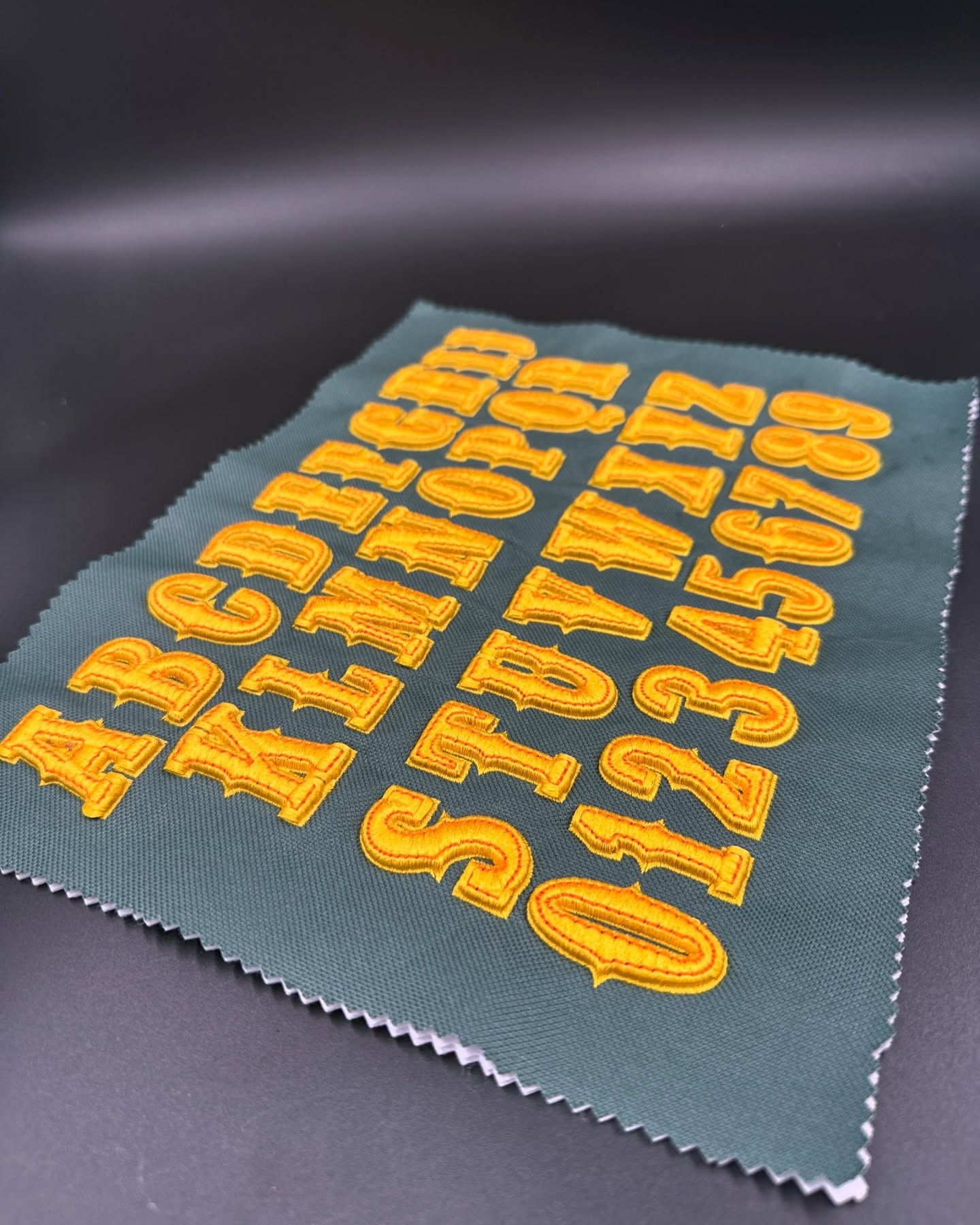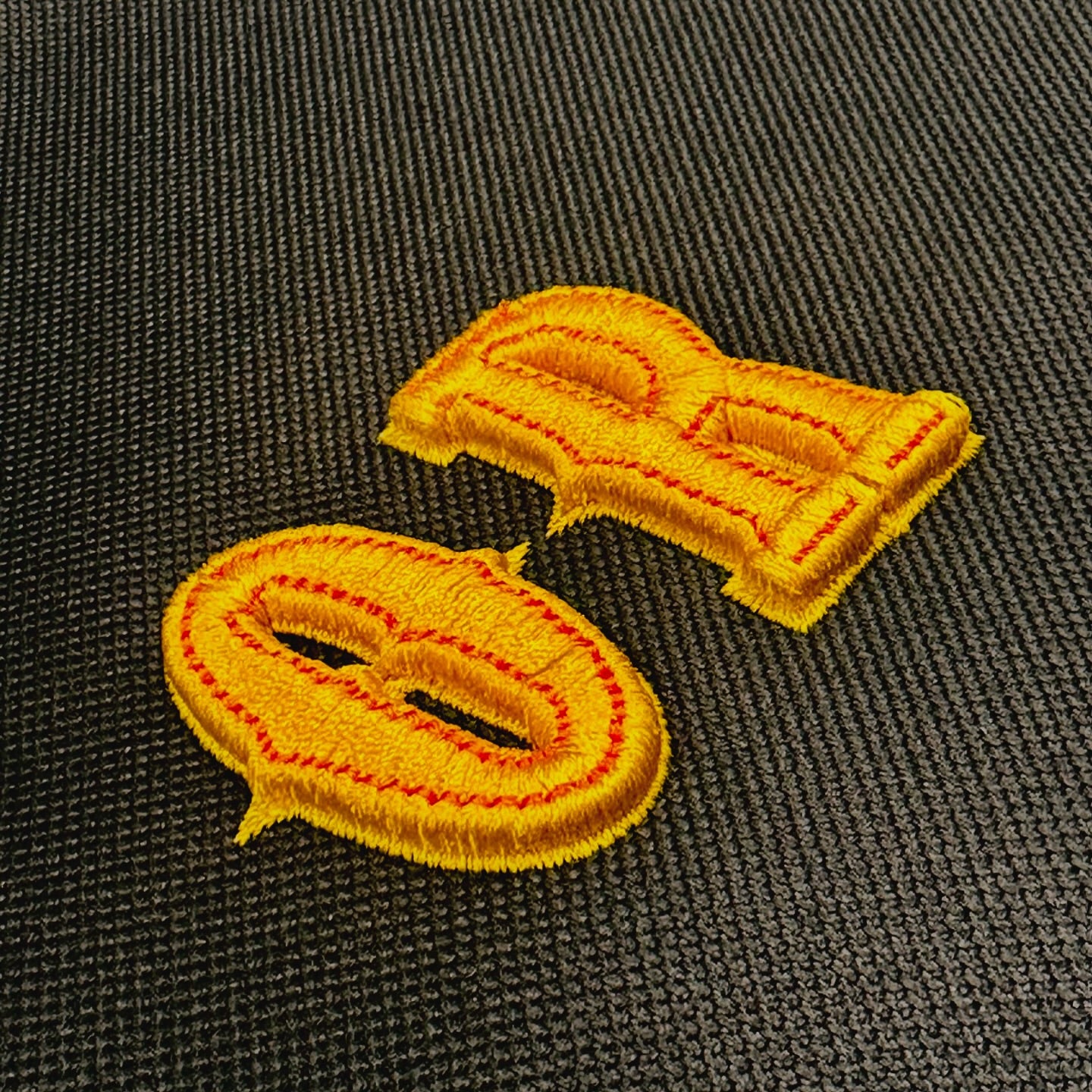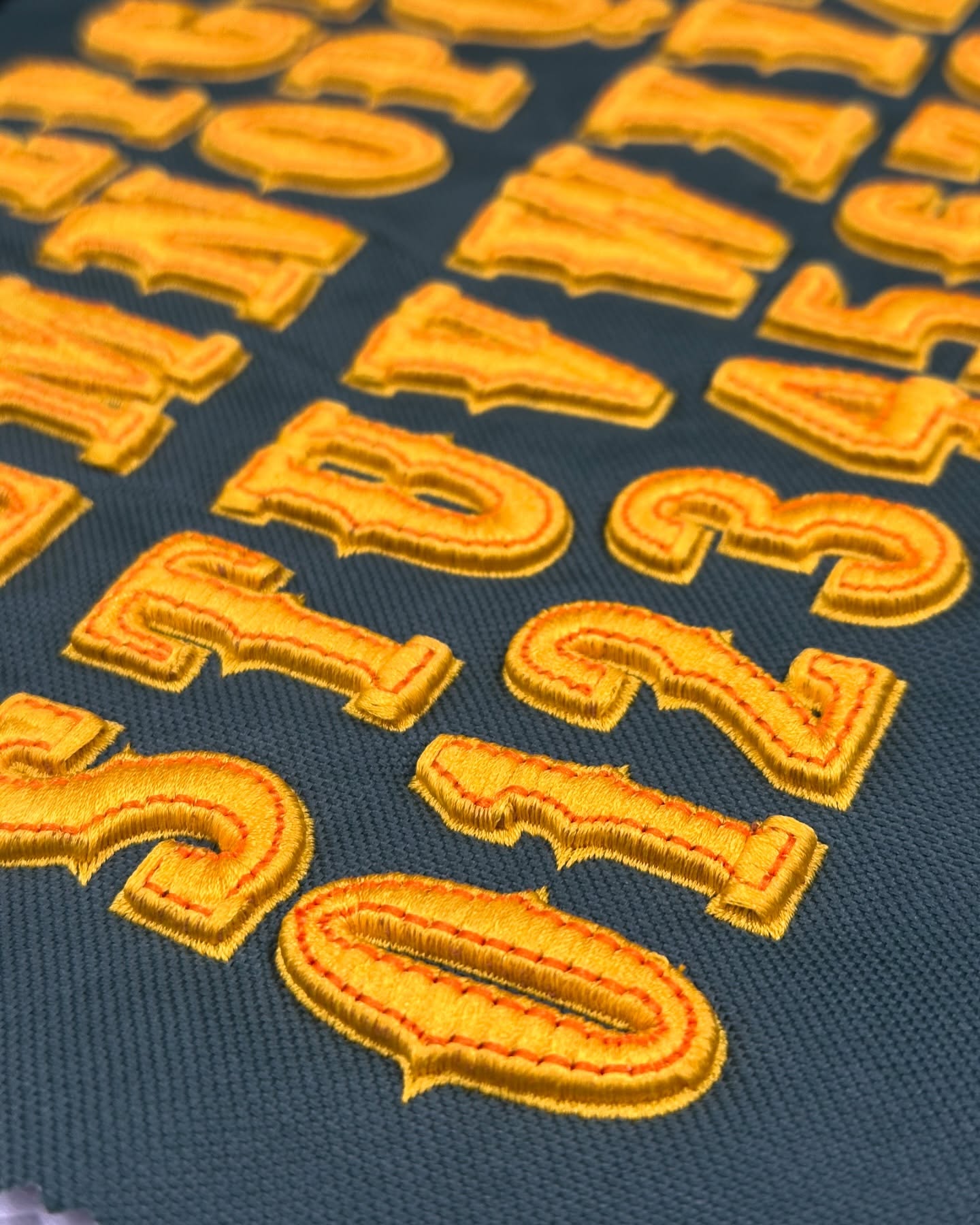
خط تطريز Western Rodeo – أحرف وأرقام عتيقة جريئة
خيوط متعددة الأوجه: حيث تتألق الحروف كالألماس ✨
قم بتحويل النص العادي إلى فن يمكن ارتداؤه بشكل مذهل باستخدام تطريز فاخر بخطوط ماسية . مستوحى من الزوايا الدقيقة للأحجار الكريمة المقطوعة، كل حرف ورقم من الأبجدية مطرز بدقة بخيوط ثقيلة، مما يخلق جوانب هندسية حادة تلتقط الضوء وتعكسه.
تجربة تألق لا مثيل لها:
💎 حافة مستوحاة من المجوهرات: تعمل الخياطة الحديثة ذات الزوايا على رفع مستوى التطريز التقليدي.
🛠️ دقة الحرفيين: يتم توجيه كل قطعة يدويًا لتحقيق محاذاة وعمق لا تشوبه شائبة.
⚡️نقي ومتين: تضمن الخيوط الثقيلة خطوطًا جريئة تدوم على القبعات والسترات والحقائب والجينز والأقمشة الفاخرة.
🎨 رفاهية متعددة الاستخدامات: يقدم بيانًا حول ملابس الشارع، ويرفع مستوى السترات، أو يضفي طابعًا شخصيًا على الهدايا التذكارية.
من الألوان الأحادية الأنيقة إلى الألوان المعدنية المبهرة - قم بتطريز إرثك بالضوء.